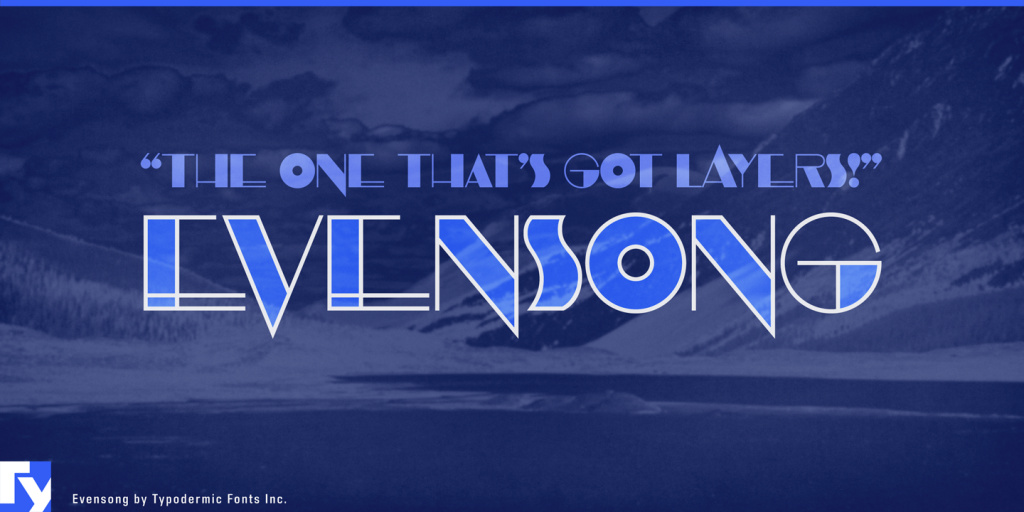
Evensong Fonts
A fonte Evensong é uma elegante tipografia geométrica que combina sofisticação com modernidade. Desenhada pelo designer Hamilton, essa fonte retro oferece uma gama de estilos, incluindo Solid e Hollow, permitindo-lhe criar texturas interessantes ou simplesmente adicionar profundidade aos seus projetos. Evensong é uma escolha perfeita para aqueles que buscam um visual minimalista e sofisticado, sendo particularmente útil para aplicações linguísticas mais complexas, como alemão, grego, vietnamita, cirílico e várias línguas baseadas em latim. Um dos destaques da Evensong é sua capacidade de suportar uma ampla variedade de idiomas, tornando-a perfeita para projetos internacionais. Além disso, a versão licenciada para desktop do Hollow estilo Evensong está disponível gratuitamente, tornando-o um investimento lucrativo e versátil. Se você é um designer buscando criar designs profundos e elegantes que abrangam uma ampla gama de idiomas, Evensong pode ser a escolha perfeita para seu trabalho.